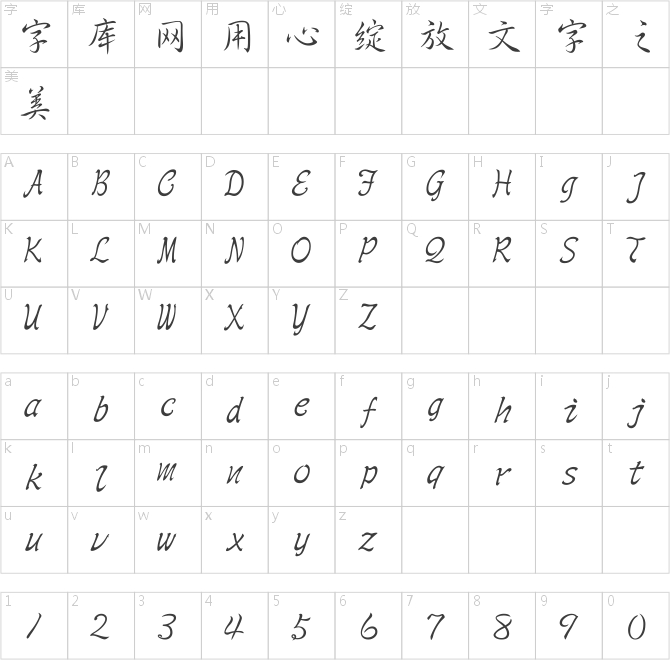
文鼎中行書簡繁 詳情頁
字體名稱: 文鼎中行書簡繁
文鼎中行書簡體繁體合并形成,兼容新版win10
更新Power TrueType Version 5.0版,和原Power TrueType Version 4.0或Power TrueType Version 4.5版本相比又將原Power TrueType big5的擴展471個外字集的部分沒有映射字碼點的漢字進行了對號入座,并修復『?』字誤映射到『抝』字位置的錯誤。
文鼎中行書簡繁字體字庫是一款讓人賞心悅目、百看不厭的中文字體,適合各類廣告和產品包裝設計應用,字體大小17.44MB,格式為ttf字體,上傳用戶是伊寧,作者/版權方為文鼎字庫